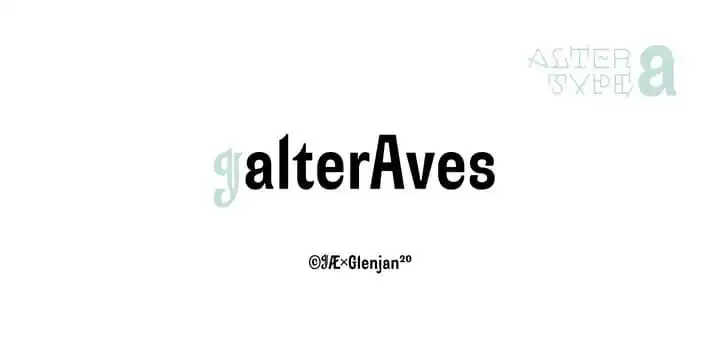
A Alter Aves Sans Serif Font é uma fonte sans-serif que abrange letras maiúsculas e minúsculas, números e sinais de pontuação. Desenvolvida por Glen Jan, esta fonte é um tipo de exibição com contração de linhas retas. Ela inclui elementos geométricos-redondos, elementos serifados-estilizados e traços de pincel flatos. Esta fonte é perfeita para quem busca uma tipografia moderna e versátil, ideal tanto para aplicativos digitais quanto impressos. Para os amantes de design gráfico, ela oferece um conjunto de letras elegante que brilha em qualquer projeto.